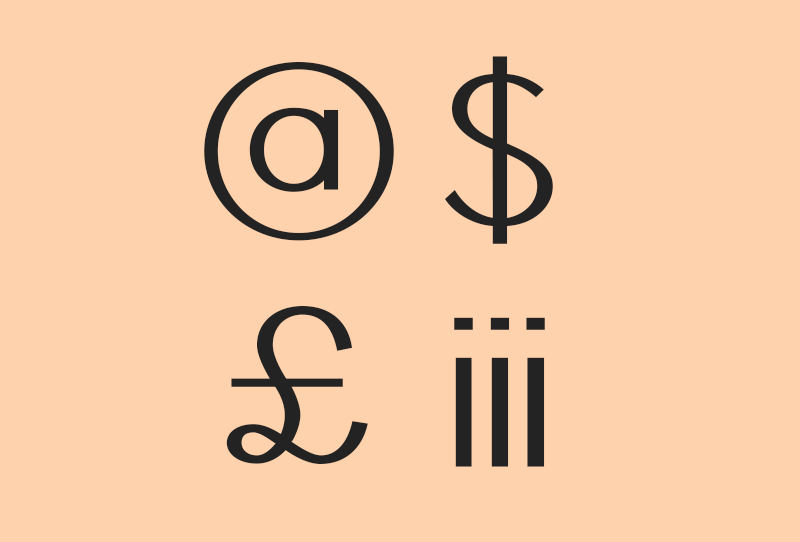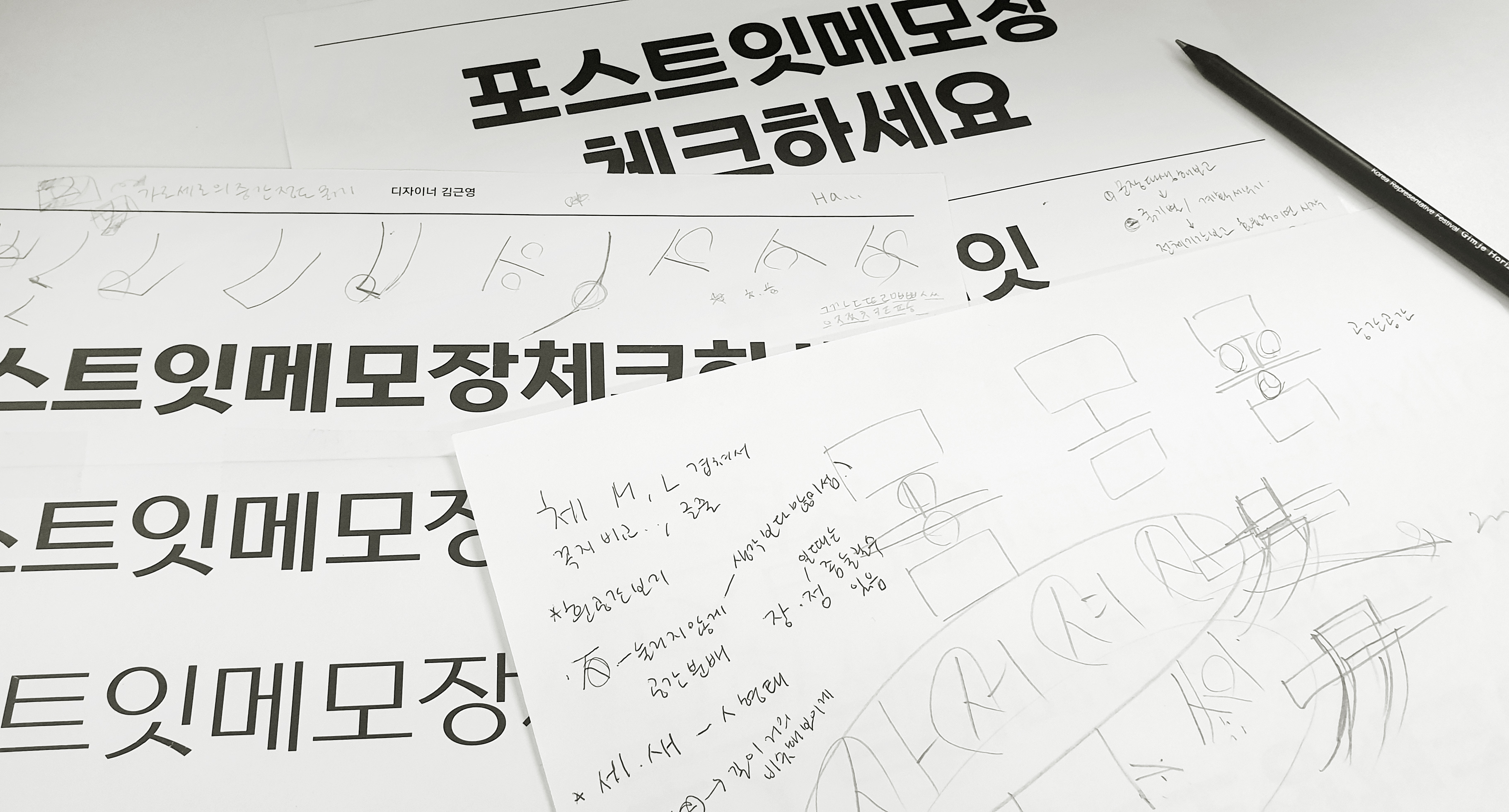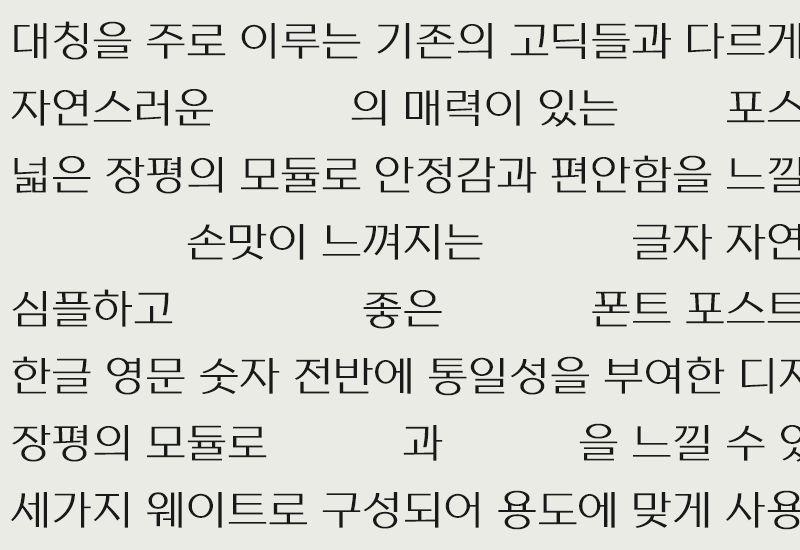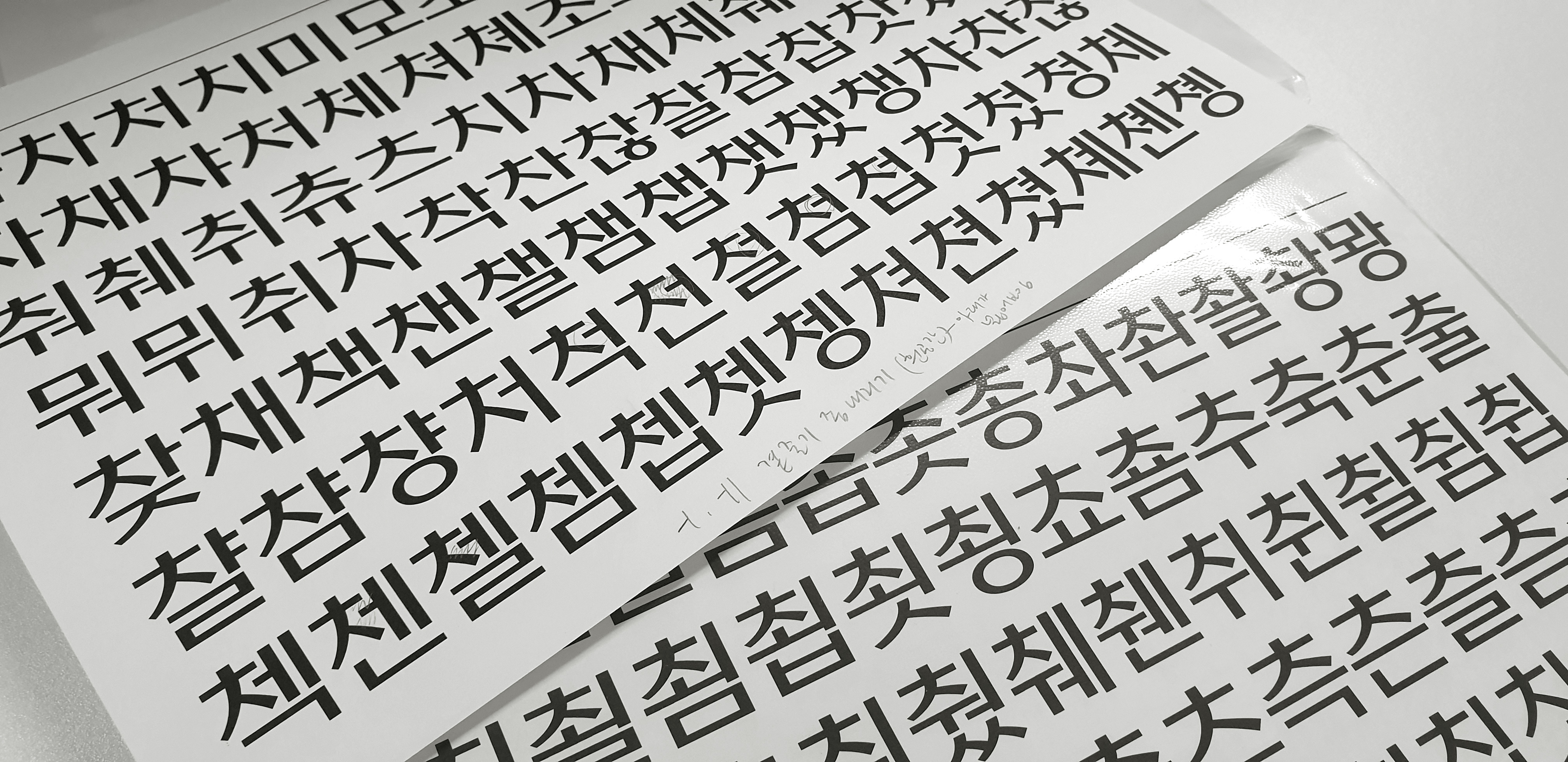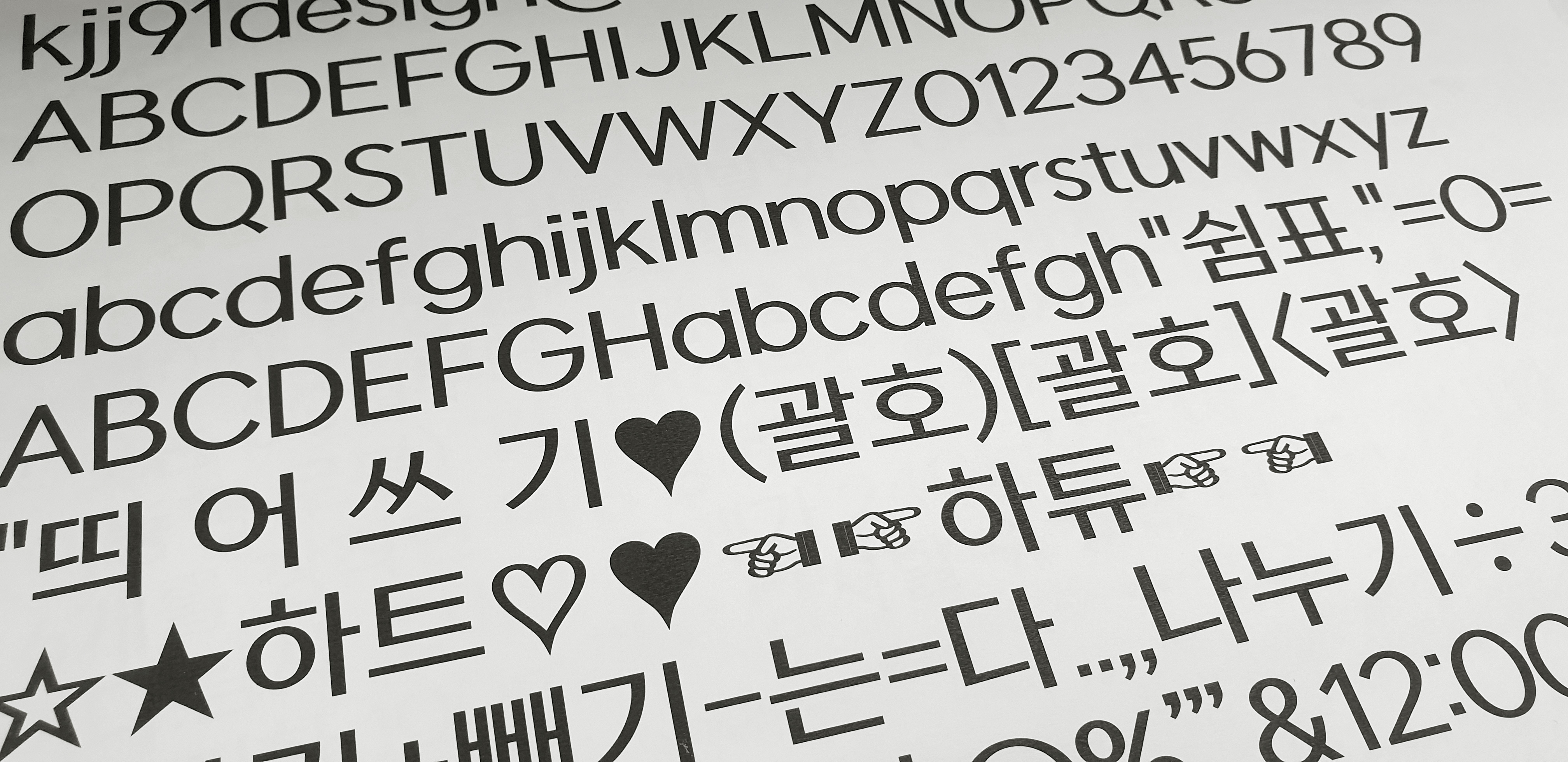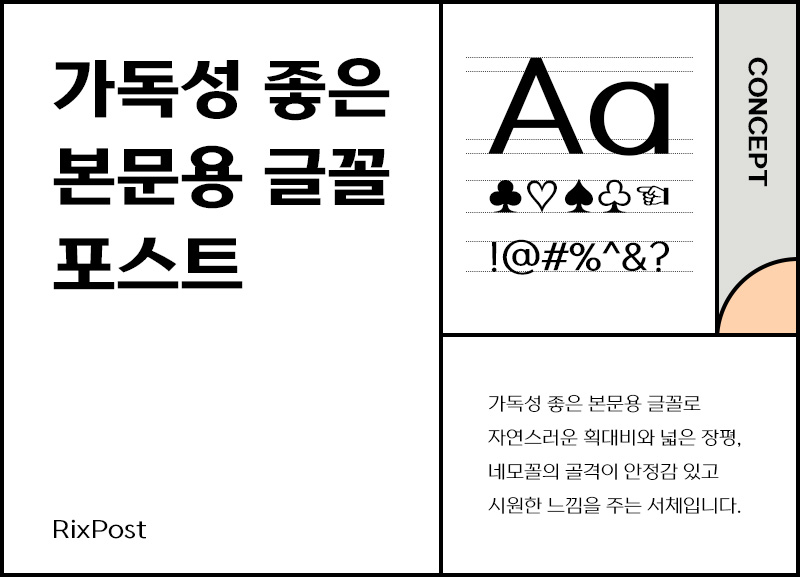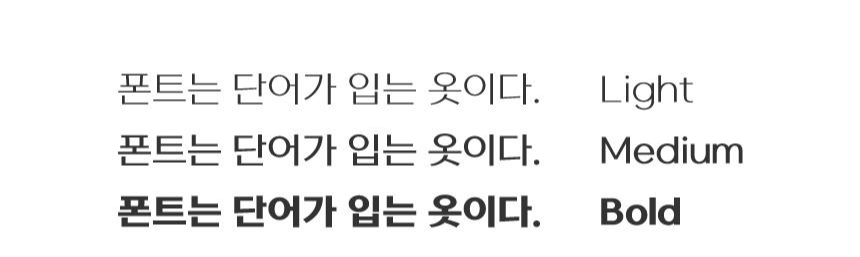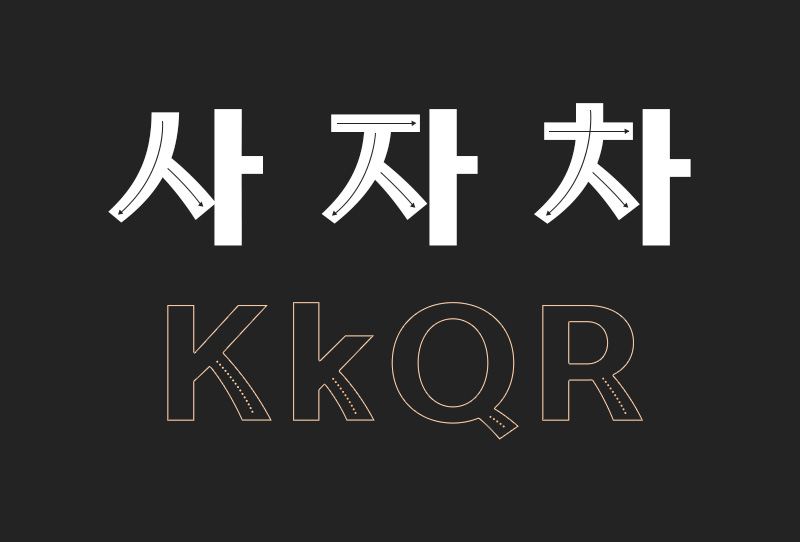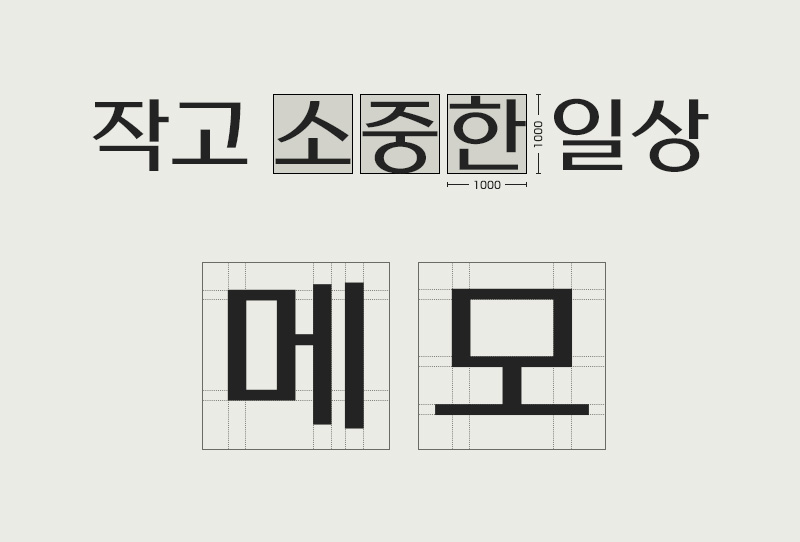
선선한 가을 날씨와 함께 찾아온 10월의 신서체를 소개합니다. 고딕은 고딕인데 너무 산뜻한 거 아닌가 싶은 신선한 폰트! 이름도 왠지 시원한 느낌이 드는「Rix포스트」입니다. 모던하고 세련된 느낌이 초기 기획부터 아주 기대가 되었던 서체인데요~ 제작자인 김근영 디자이너와의 인터뷰 먼저 보고 가실게요:)
폰트를 알려면 디자이너를 알아야지_폰트 디자이너 인터뷰
안녕하세요, 근영 디자이너님. Rix코코 이후에 오랜만에 새로운 폰트로 다시 만나니 반갑네요! 이번 신서체는 어떤 폰트인지 소개해 주실 수 있나요?
이번에 만나게 될 'Rix포스트' 친구는 산뜻한 발걸음을 가진 친구예요! 본문과 제목에 모두 쓰일 수 있고요. 평체의 골격으로 안정감이 있고 시원해요. 자연스러운 획대비와 특정 자소들에 손맛이 담긴 것이 특징입니다. 굵기는 3종류예요. 두근두근~~~
폰트명이 다양한 뜻을 가진 단어네요, 어떻게 기획하게 된 폰트인가요?
저의 첫 번째 친구였던 발랄하고 귀염미 넘치는 Rix코코는 두꺼운 손글씨 스타일의 제목용 폰트였는데요. 이번엔 코코랑 반대되는 친구를 만들어보자 했어요. 코코와는 다르게 차분한 친구를 생각해보다가 그럼 또 너무 진지해지지 않을까? 어딘가 산뜻하고 밝아 보일 수 있는, 고런 친구를 상상했어용!
그래서 본문에도 쓰일 수 있는 고딕 폰트로 정했고 기존의 고딕들과 차별화되도록 손맛을 담아보려고 했어요! 질문에 언급해 주신 것처럼 '포스트'라는 단어에는 다양한 의미들이 있는데요, 우편물, 편지, 게시글(소셜 네트워크 등에 올리는) 등등. 이런 의미처럼 어딘가에 글을 게시하다, 쓰다 같은 느낌이 폰트와 잘 어울린다고 느껴졌답니당!
폰트를 만들 때 특별히 신경 쓰는 부분이 있다면?
제가 평소에 부드럽고 안정감 있는, 편안한 분위기가 나는 폰트들을 좋아해요. 그래서인지 요번 폰트도 그런 분위기가 나도록 신경을 써서 제작하게 된 것 같아요.
제작자로서 'Rix포스트'의 가장 매력적인 부분은 무엇이라고 생각하시나요?
어딘가(?) 알게 모르게(?) 은근슬쩍(?) 사람 냄새나는 고딕이라고 할까요? 차분한 사람 같아 보이기도 해요. 대칭을 주로 이루는 고딕들과 다르게, 대칭을 이루지 않는 획들을 조합해 자연스러운 느낌을 주는 것이 매력이에요!
마지막으로, 이 폰트가 어떻게 쓰였으면 좋겠나요?
Rix포스트와 함께 산뜻하게 걸어보시는 거 어떠신가요~?! 글자가 시원하고 편안해서 팸플릿이나 브로슈어 타이틀에 쓰기 좋을 것 같아요. 고급스러운 느낌의 디자인과도 잘 어울릴 것 같고요, 본문용 텍스트로서 가독성도 좋기 때문에 책에도 많이 사용되면 좋겠습니다.
#쓰고 또 써보기
수정을 하면 할수록 좋은 글이 탄생하듯, 폰트도 다듬고 다듬고 또 다듬는 과정이 필요합니다. 그래서 디자이너들은 계속 '쓰기'를 반복하죠. 그 과정에서 뭔가 부자연스럽거나 공간 분배가 아쉬운 부분을 발견하면 또 여러 번의 수정을 거칩니다. 최종 완성본이 나오기까지 계속해서 써보고 수정하는 과정은 더 좋은 폰트를 만듭니다.
#컨셉과 스토리
폰트를 보고, 또 직접 써보고 떠오르는 단어들을 마인드맵으로 그려봅니다. 여러 디자이너들이 머리를 모아 단어들을 던지고, 컨셉을 잡아갑니다. Rix포스트 폰트는 견고하지만 자연스럽고, 담백하면서 시원한 감정을 이끌어내 주었습니다.
시원하고 산뜻한 고딕
산뜻하다 [사전적 정의]
1. 기분이나 느낌이 깨끗하고 시원하다.
2. 보기에 시원스럽고 말쑥하다.
이번 신서체는 수식어가 참 많은데요. 산뜻한 고딕, 손맛이 담긴 고딕, 편안한 고딕 등 모두 포스트 폰트를 보면 느껴지는 단어들입니다. 그중에서도 단연 '산뜻하다'라는 형용사는 이보다 더 폰트에 대한 느낌을 잘 표현해 줄 수 있는 말이 있을까 싶은 수식어예요. 보기에도 그렇지만 써보면 더더욱, 서체 자체에서 산뜻함이 느껴집니다. 아무래도 가장 얇은 Rix포스트 Light가 제일 공간감이 많이 느껴져 시원하고, 웨이트가 굵어질수록 단단하고 견고한 고딕의 느낌이 납니다. 굵기는 총 3종.
들어는 봤나, 손맛 담긴 고딕
김근영 디자이너도 손맛이 담긴 고딕이라는 말을 여러 번 강조해 주셨는데요~ 대부분의 고딕이 일정한 굵기의 획을 갖고 있는 것과 달리 Rix포스트는 끝으로 갈수록 얇아지거나 두꺼워지는 ㅅ, ㅈ, ㅊ 꼴의 형태적 특징을 볼 수 있습니다. 고딕으로써 독특한 부분이기도 하고, 영문 디자인에도 반영되어 더욱 매력적으로 느껴지는 부분입니다.
편안하고 차분한 친구
네모 틀 안에 넓은 장평으로 안정감 있고, 가로 획과 세로 획의 자연스러운 대비가 텍스트만으로도 충분한 존재감을 발산합니다. 글줄이 일정해 편안하고 차분한 분위기를 주며 왠지 모를 신뢰감을 주는 친구입니다.
개인적으로 영어로 쓴 글씨가 특히나 맘에 드는 폰트입니다. (모던하고 세련된 느낌이 쓸수록 너무 예쁘답니다!) 특수문자들도 서체의 특징을 살려서 획대비가 들어가 있고, 전화기(☎) 모양이 저렇게 스마트폰 모양으로 표현되는 깜찍함까지. 아주 트렌디하죠.
| Rix포스트 적용 이미지 샘플
Rix포스트는 가독성 좋은 본문용 글꼴입니다. 대칭을 주로 이루는 기존의 고딕들과 달리 조금은 사람 냄새가 나는 자연스러움을 주는 서체라고 할 수 있죠. 기본적으로 책, 포스터, 팸플릿 등 텍스트가 많이 필요한 곳에 잘 어울리며, 다양한 웹, 그래픽 디자인 콘텐츠에도 유용하게 쓰일 것으로 보입니다.